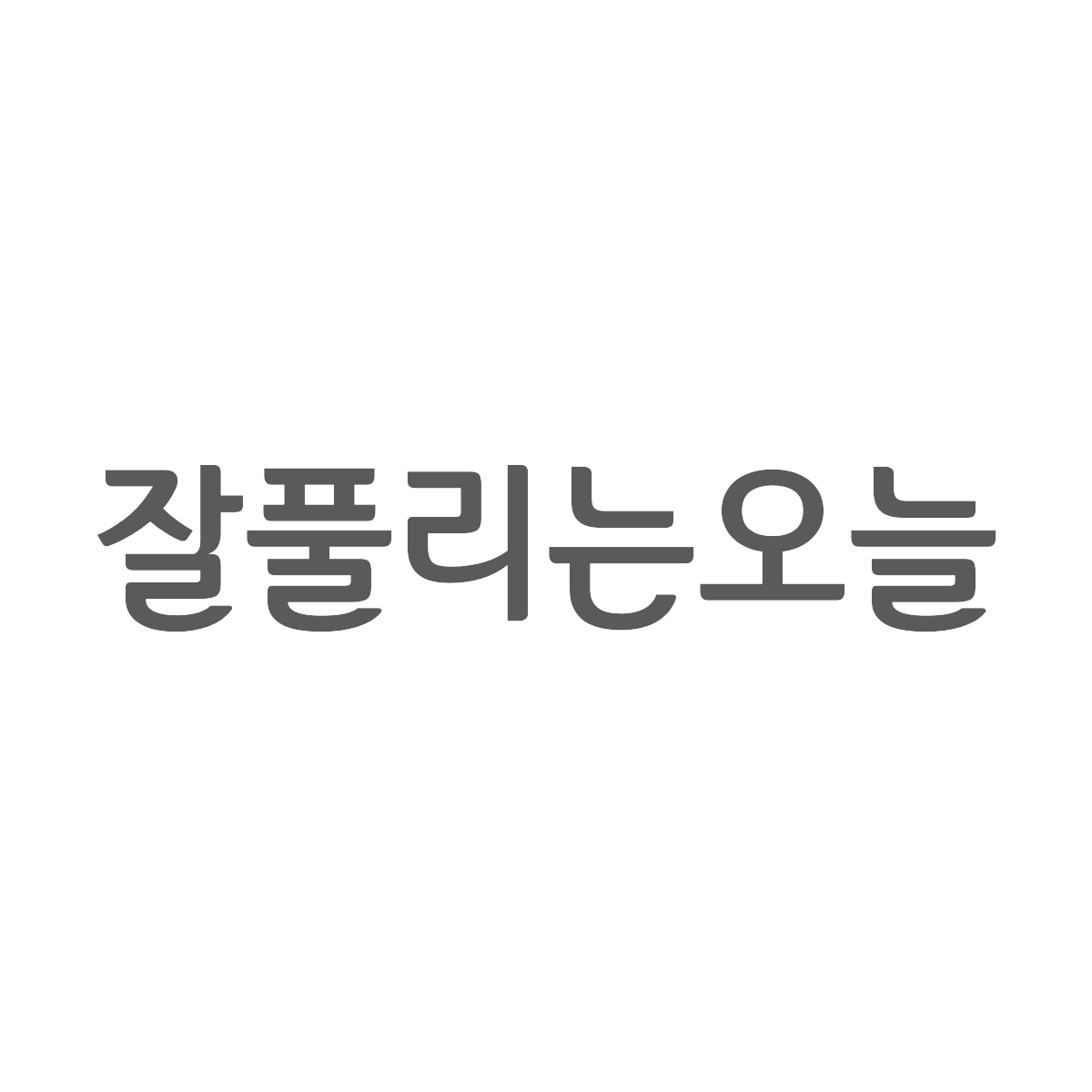
잘풀리는오늘
잘풀리는집 전용 서체는 잘풀리는집 로고를 바탕으로 깔끔하고 독특한 룩앤필을 재현하였으며 가독성을 살리기 위해 모듈의 충분한 공간 활용을 적용하였습니다. 제목이나 로고형으로 사용하기 좋은 '잘풀리는 오늘'체와 본문형으로 사용하기 좋은 '잘풀리는 하루'체 두 종류의 서체를 준비하였습니다. 잘풀리는집 특유의 감성인 잘 풀릴 것 같은, 기분 좋은 느낌을 서체에 담고자 노력하였고 잘풀리는집 서체를 사용하며 보고서나 리포트, 간판 외에도 무엇이든 다 잘 될 것 같은 긍정의 마법에 걸려 승승장구 하시길 바랍니다. 창립 20주년을 기념하여 고객님들께 받은 사랑에 보답하기 위해 준비한 작은 선물로 어느 곳에나 자유롭게 사용하실 수 있으며 잘풀리는집 서체를 사용하시는 모든 분이 바라는 것들이 조금이나마 잘 풀리길 응원합니다.
- Sans,민부리